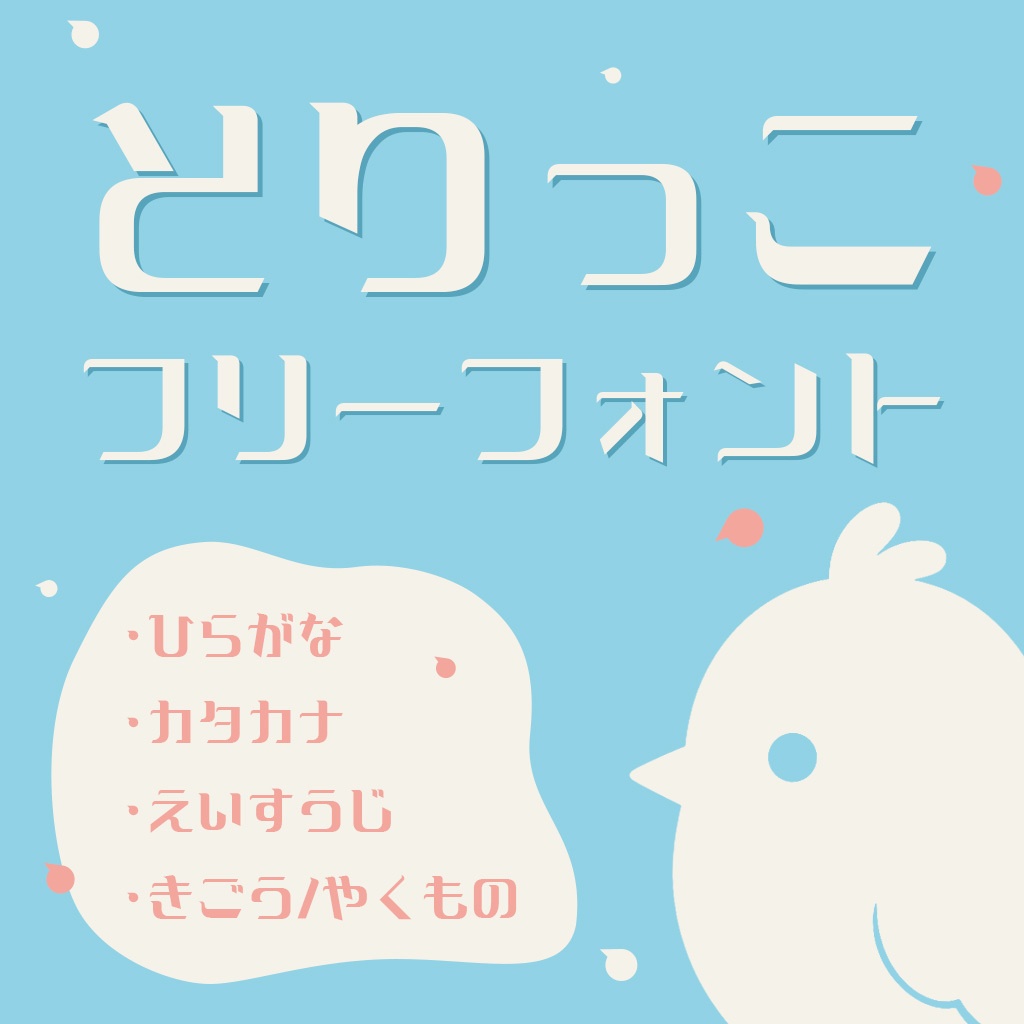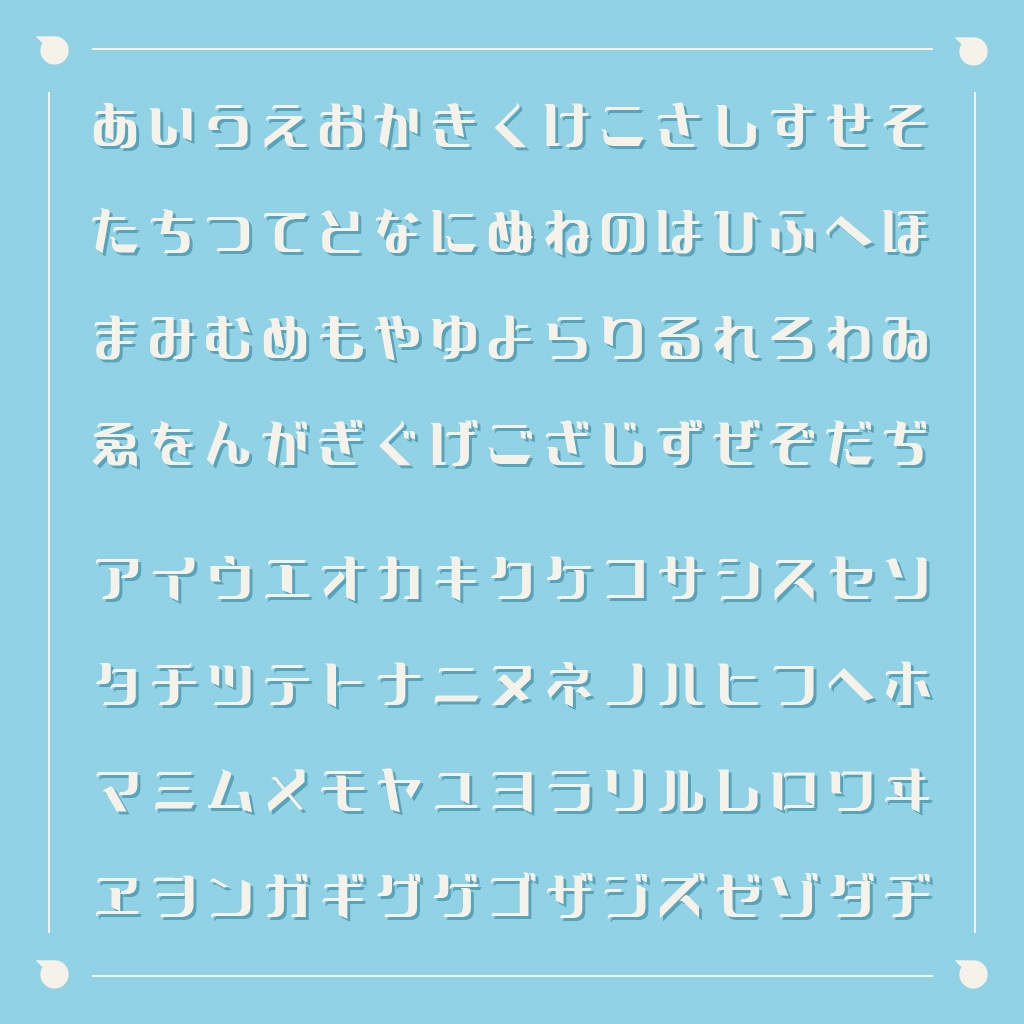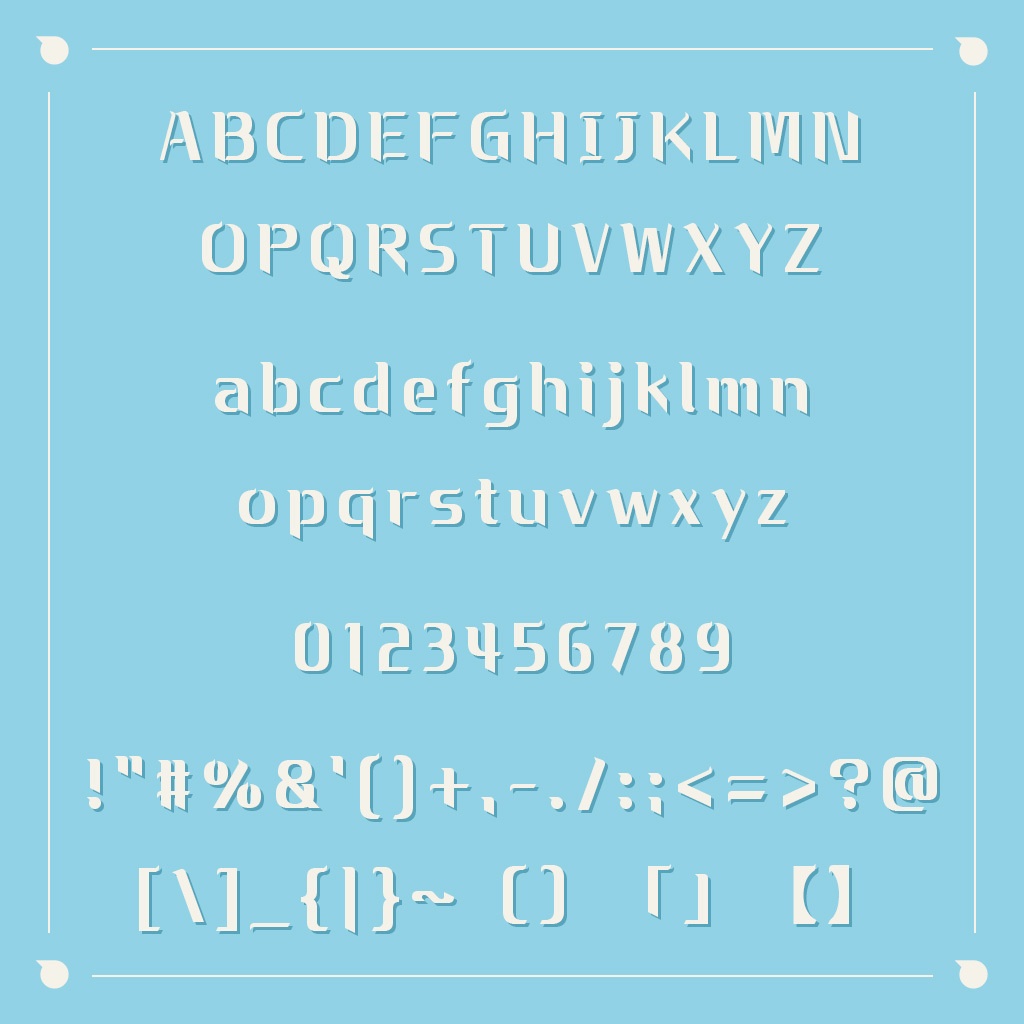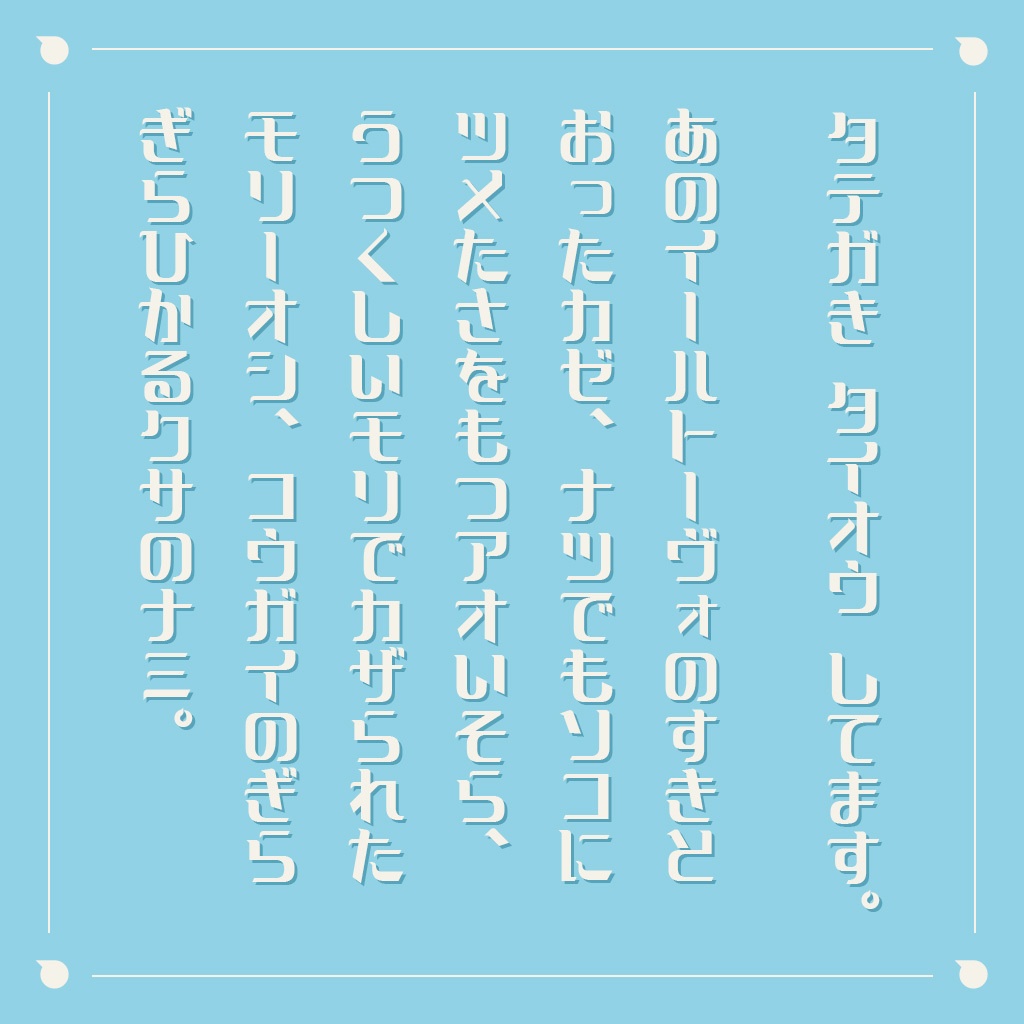
【フリーフォント・商用可】とりっこ
小鳥のくちばしのような飾りがついたフォントです。 収録文字はひらがな、カタカナ(全角)、英数字(全角・半角)、一部記号・約物です。 ★もし気に入っていただけましたら、「支援版」の購入をご検討いただけますと大変嬉しいです。 ●フォントについて バージョン:1.00 最終更新日:2026年7月18日 ファイル形式:TrueType(.ttf) ●本フォントの利用 個人利用はもちろん、商用利用も可能です。 映像や印刷物、同人活動などにご活用いただければ幸いです。 ▲注意点 ロゴへの利用は可能ですが、商標登録は禁止です。 Webフォントとしての利用、およびサーバーへのフォントファイルのアップロードは禁止します。画像化してご利用ください。 アプリやゲームへの埋め込みは、第三者がフォントデータを容易に抽出できない形式(暗号化、難読化など)を講じる場合に限り、することができます。 AI生成物への利用は可能です。しかし、フォントファイル自体の機械学習への利用(LoRA作成等)は禁止します。 ●その他禁止事項 本フォントを改変・再配布すること。 本フォントを公序良俗に反する目的、特定の個人、団体、人種、信条、性別、社会的身分などを誹謗中傷、差別、攻撃する目的で利用すること。 本フォントファイル自体を無断転売すること。 本フォントの制作者であると偽ること 本フォントファイル自体をNFT化し、取引可能な状態で発行・販売すること。 ●著作権・クレジット表記 本フォントの著作権は、制作者 Mito に帰属します。 クレジット表記は不要です。 ●免責事項 本フォントの入手・利用により発生したいかなる損害・トラブルについても、制作者は一切の責任を負いません。 ●更新履歴 ver.1.00 リリース ●お問い合わせ 不具合等がありましたら、BOOTHのメッセージからお願いします。 利用規約はたぬき侍様の「フォント利用規約ジェネレーター」(https://tanukifont.com/license-gen/)を参考に制定しました。